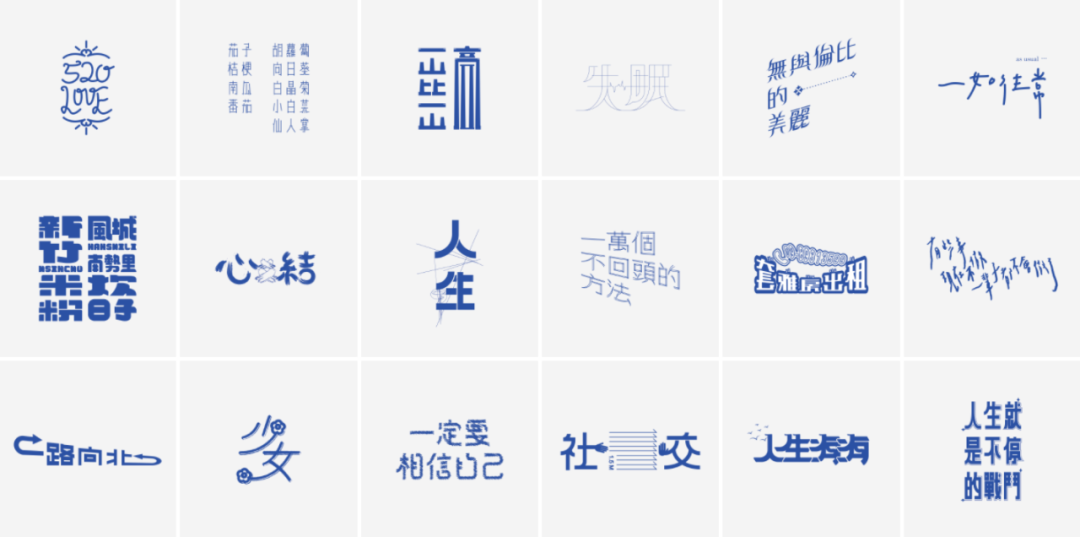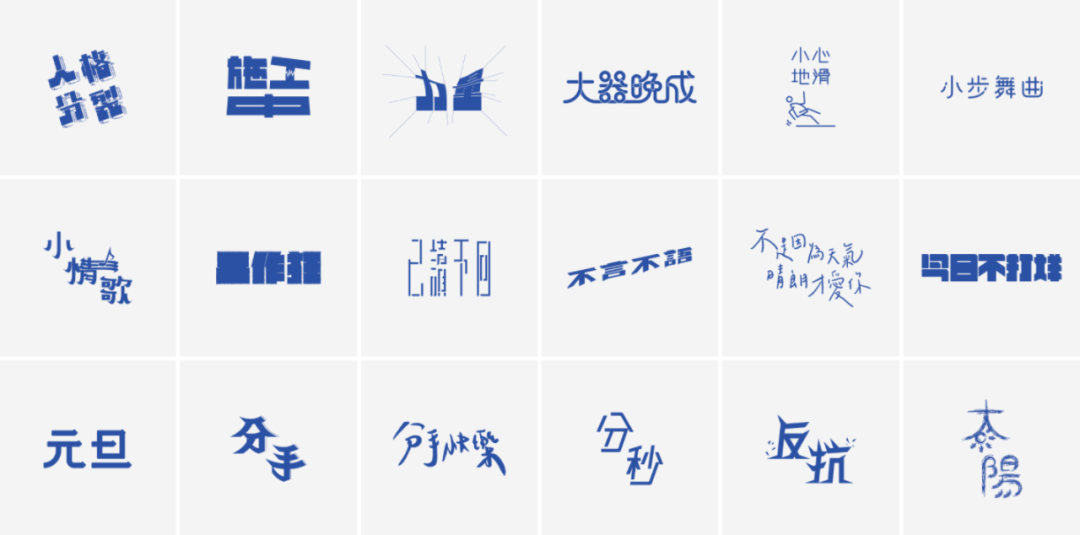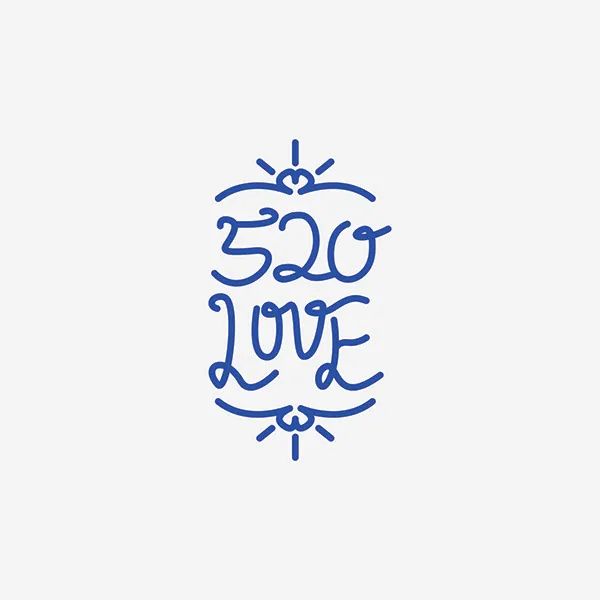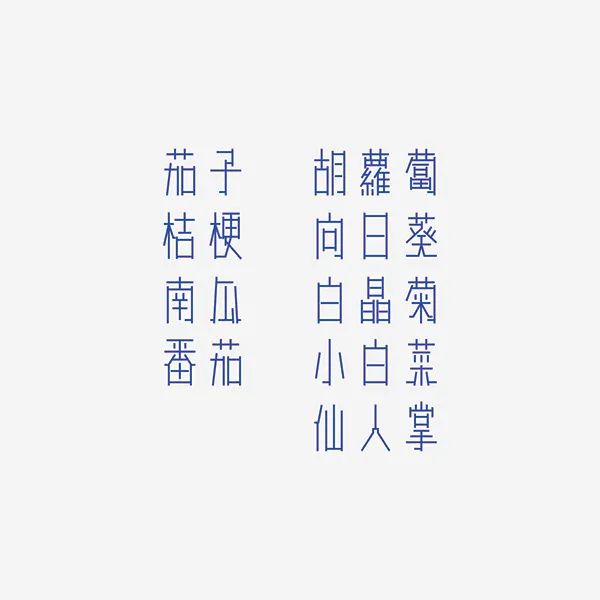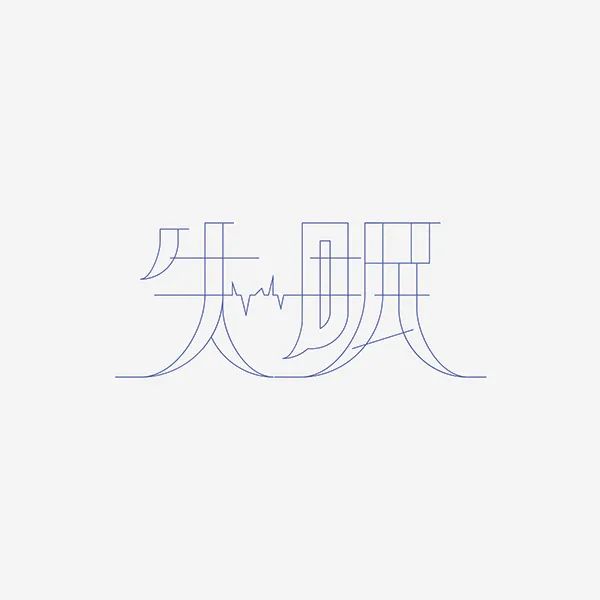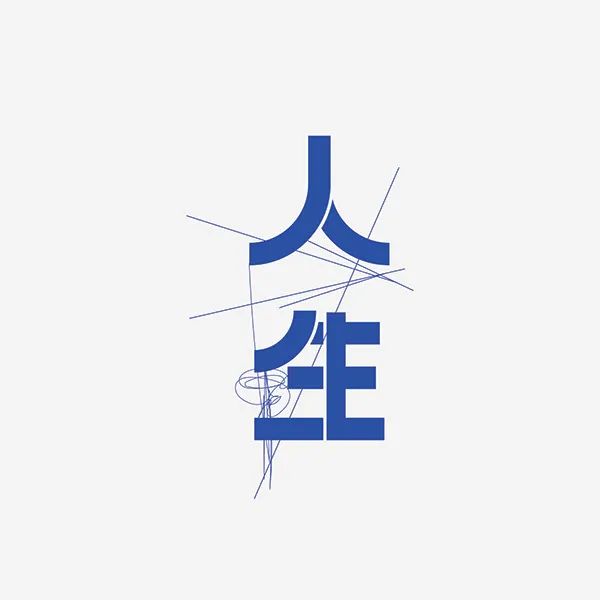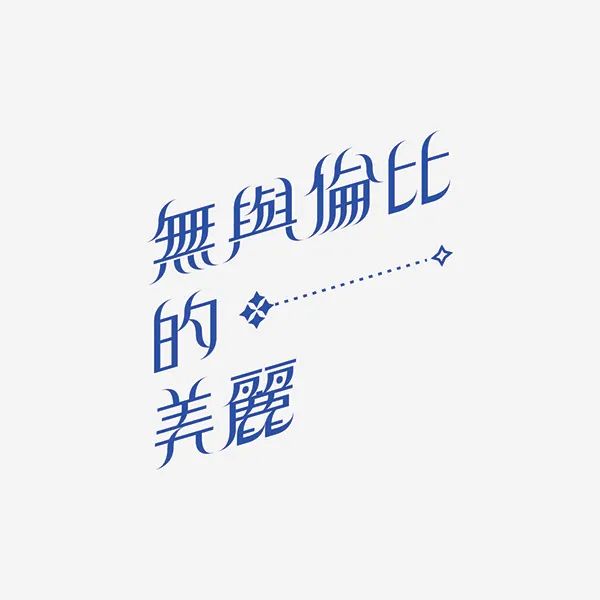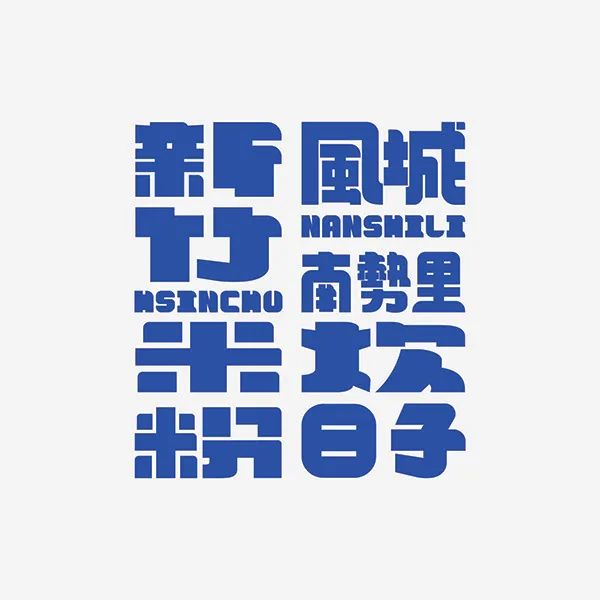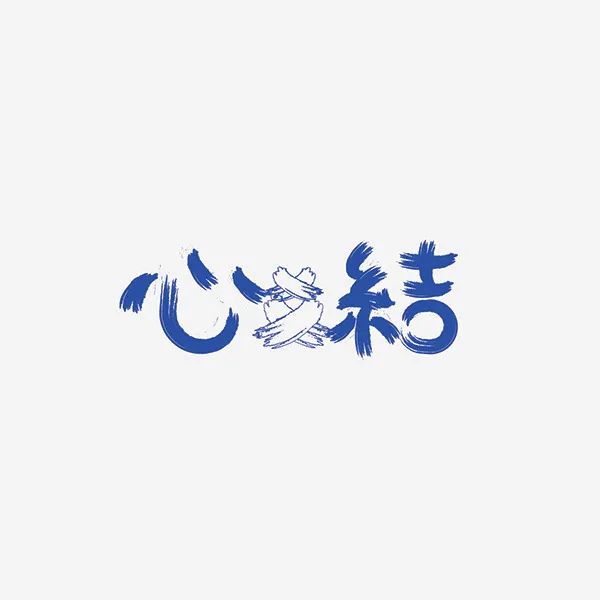
如果365天坚持做一件事,你会做些什么?
给你365天的时间做一个挑战
你会做些什么?
来自台湾设计师 pinxuan liu 的回答是
每天设计一组文字!
哎!真是没事找字做!
有些是在既有字体的基础上造型,
有些是从最基本的文字开始做起。
下面这些字体最是撩人心炫~
打破原有文字的平衡,
也是一种设计手法,
可以给文字加上有机曲线。
很多人觉得手写字体就是书法字体,
其实不然,
手写字体只不过借助了类似书法字的表现形式,
但比书法字体更适于现代设计。